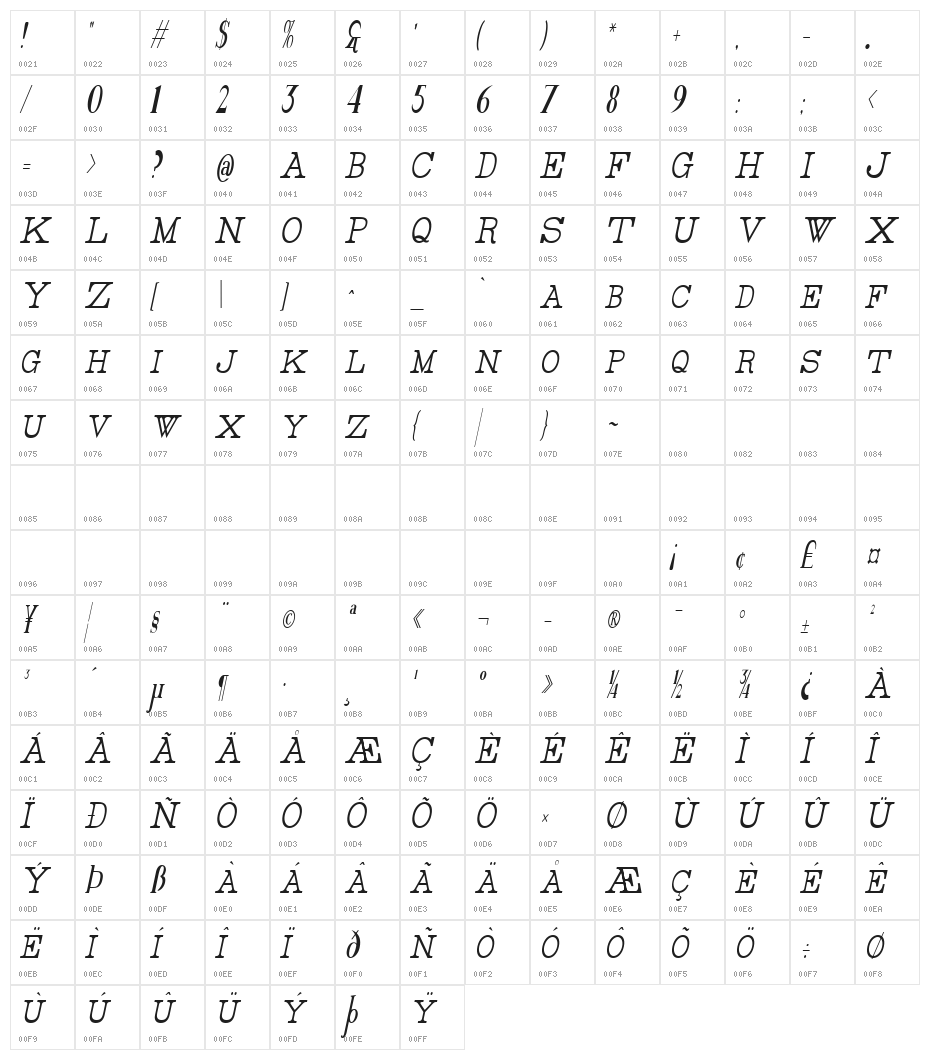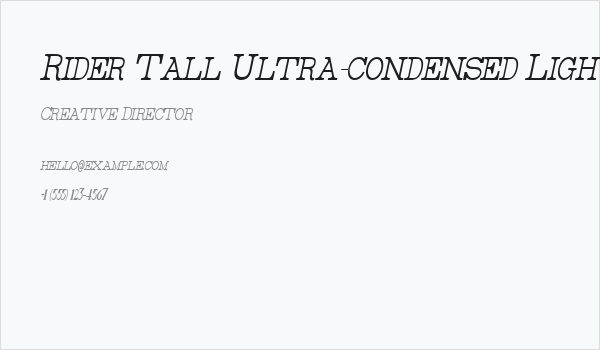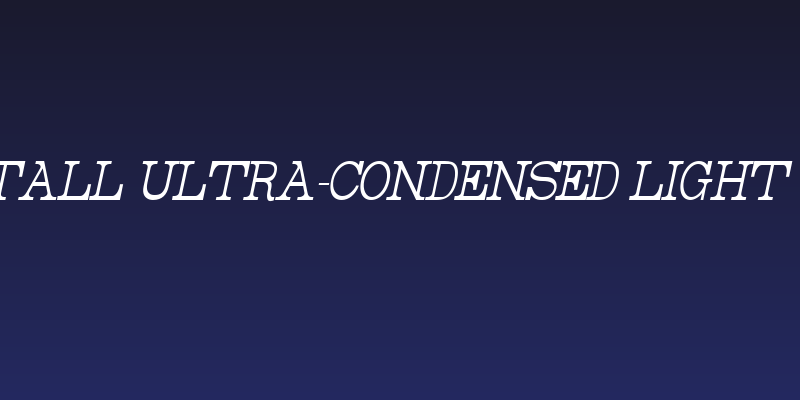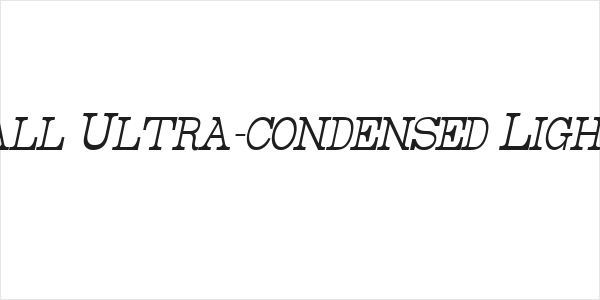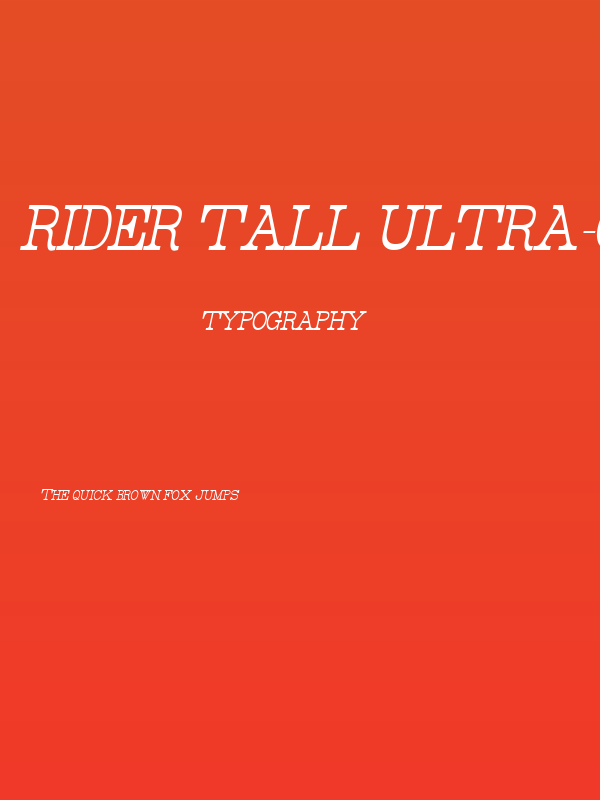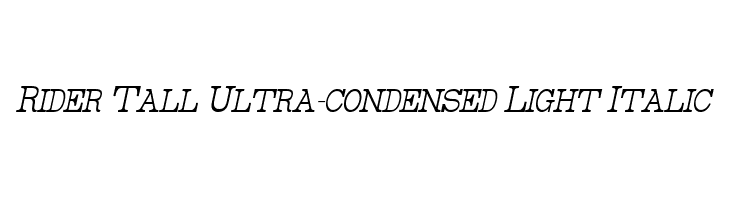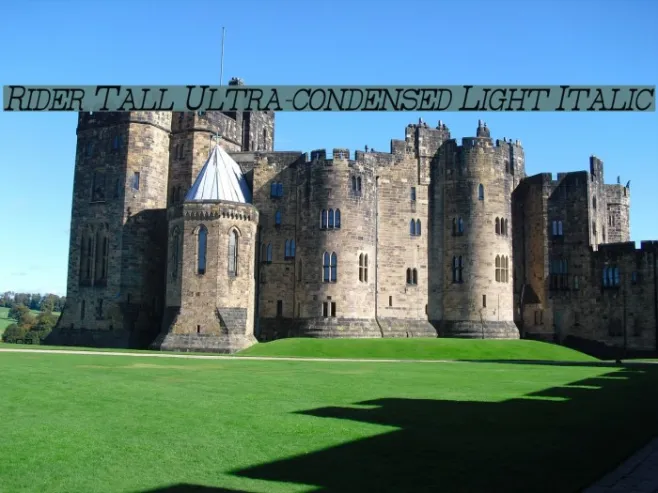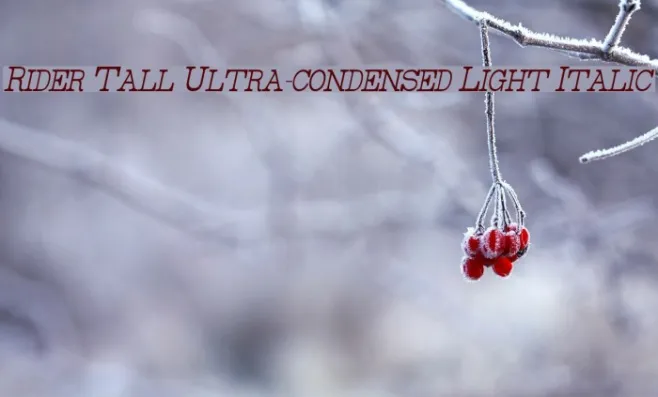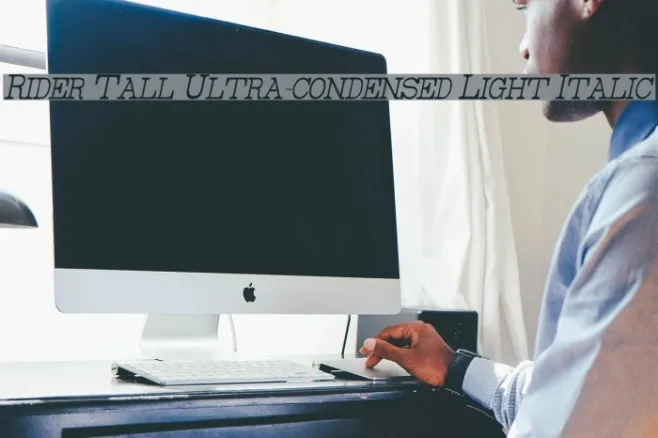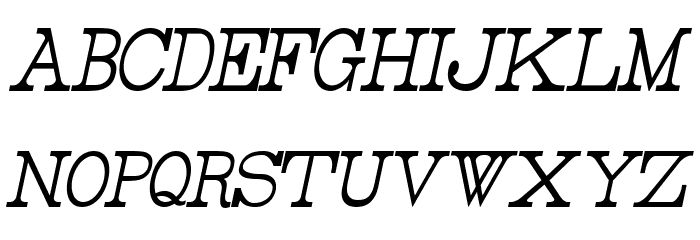
Rider Tall Ultra-condensed Light Italic Font
| Caso d'uso | Headlines, Logos, Editorials |
| Progetti proposti | Ideal for fashion magazines, luxury branding, elegant invitations, and modern editorial layouts. |